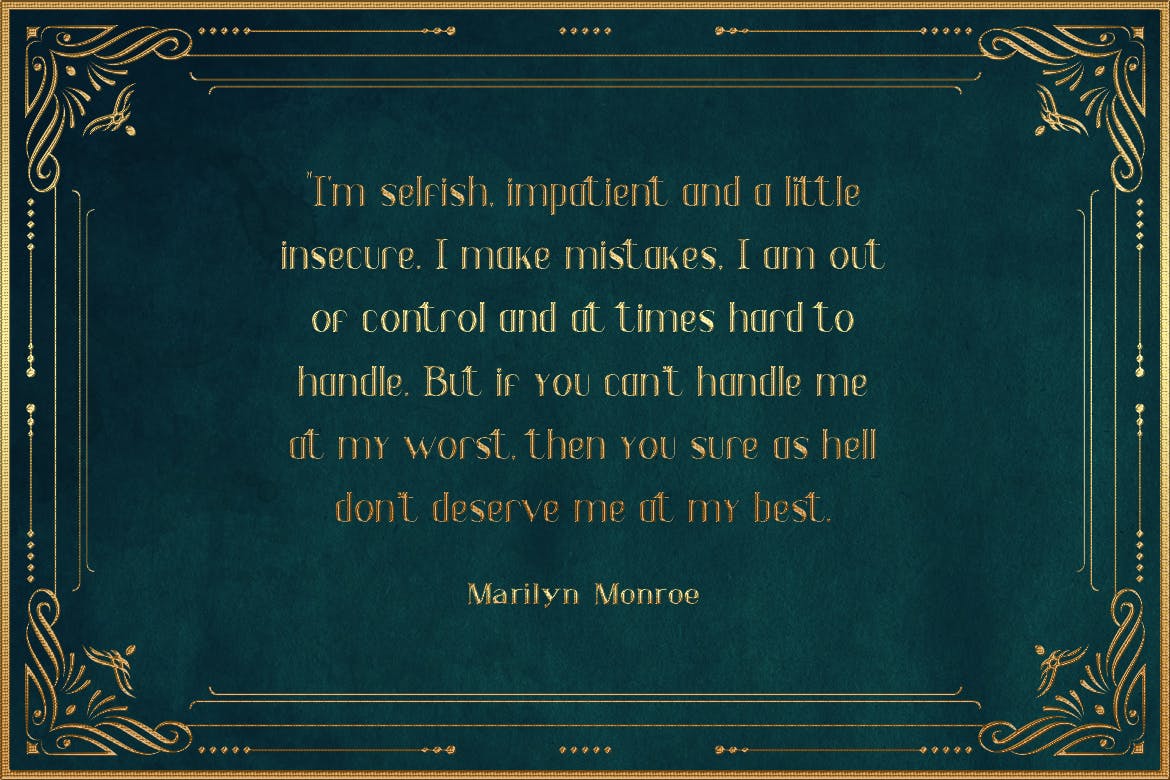
دانلود فونت Bagiewise با طراحی آرت دکو لوکس
Bagiewise Luxury Art Deco Typeface
این فونت زیبا و شیک مناسب برای پروژه‌های مختلف شماست.
فونت Bagiewise را معرفی می‌کنیم. آیا به دنبال یک فونت نمایش آرت دکو با طراحی جسور و محکم هستید که حس لوکس و vintage را داشته باشد؟ ما می‌توانیم به شما کمک کنیم! فونت آرت دکو Bagiewise را دانلود کنید. این فونت مناسب استفاده در بسیاری از مناسبت‌ها مانند دعوت‌نامه، بنر، عنوان فیلم، برند، رویداد و بسیاری موارد دیگر است :)